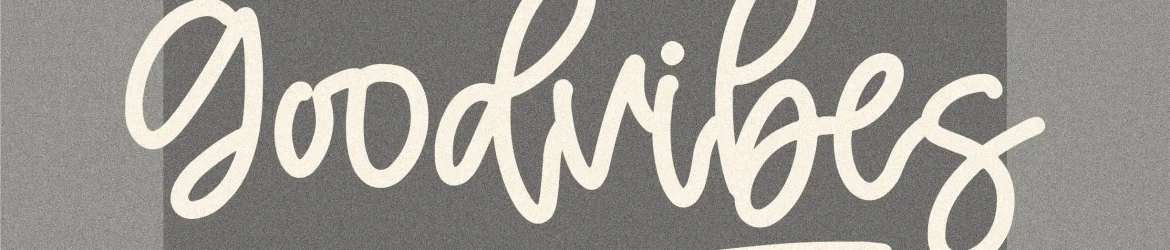
Goodvibes Font – Download Grátis
Esta é uma fonte escrita a mão desenvolvida por perspectype, perfeita para projetos variados, como logotipos, projetos de marca, designs de casa de banho, embalagens de produtos, xícaras, citações, postais, sacolas de shopping, camisetas, capas de livro, cartões de nome, convites, cartões de visita, cartões de agradecimento, etiquetas, fotografia e até mesmo assinaturas. A fonte Goodvibes captura a essência da escrita espontânea, trazendo à vida um toque autêntico que se ajusta perfeitamente para seus projetos em busca de uma aura elegante e personalizada. Seja para um design de logotipo inspirado no movimento do seu negócio ou para um projeto gráfico mais casual como cartões de visita, esta fonte escrita a mão oferece a sensação de autenticidade que você precisa para seus projetos. Goodvibes é ideal para aqueles que procuram introduzir uma pitada única e quase mágica em qualquer design que escolham desenvolver.